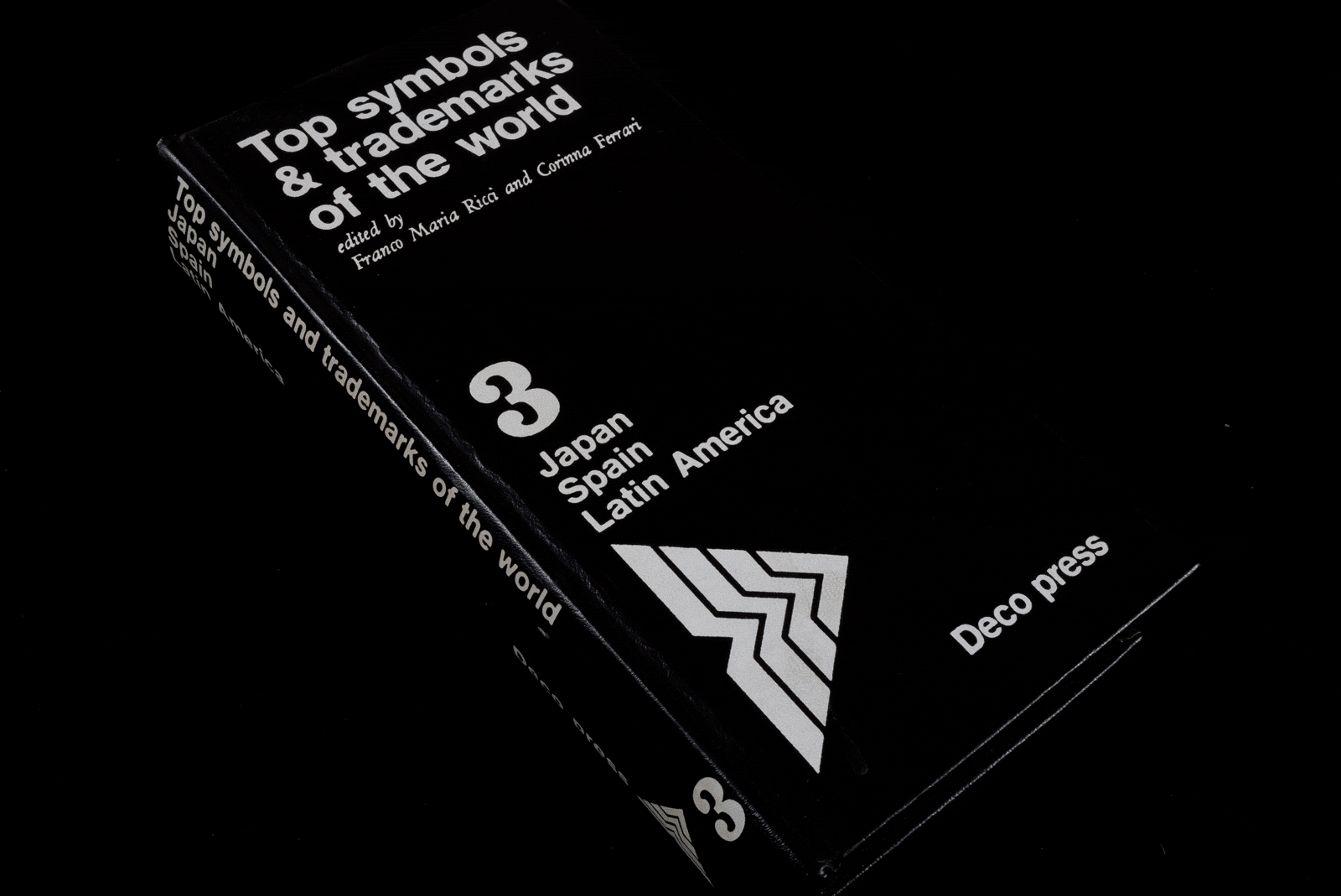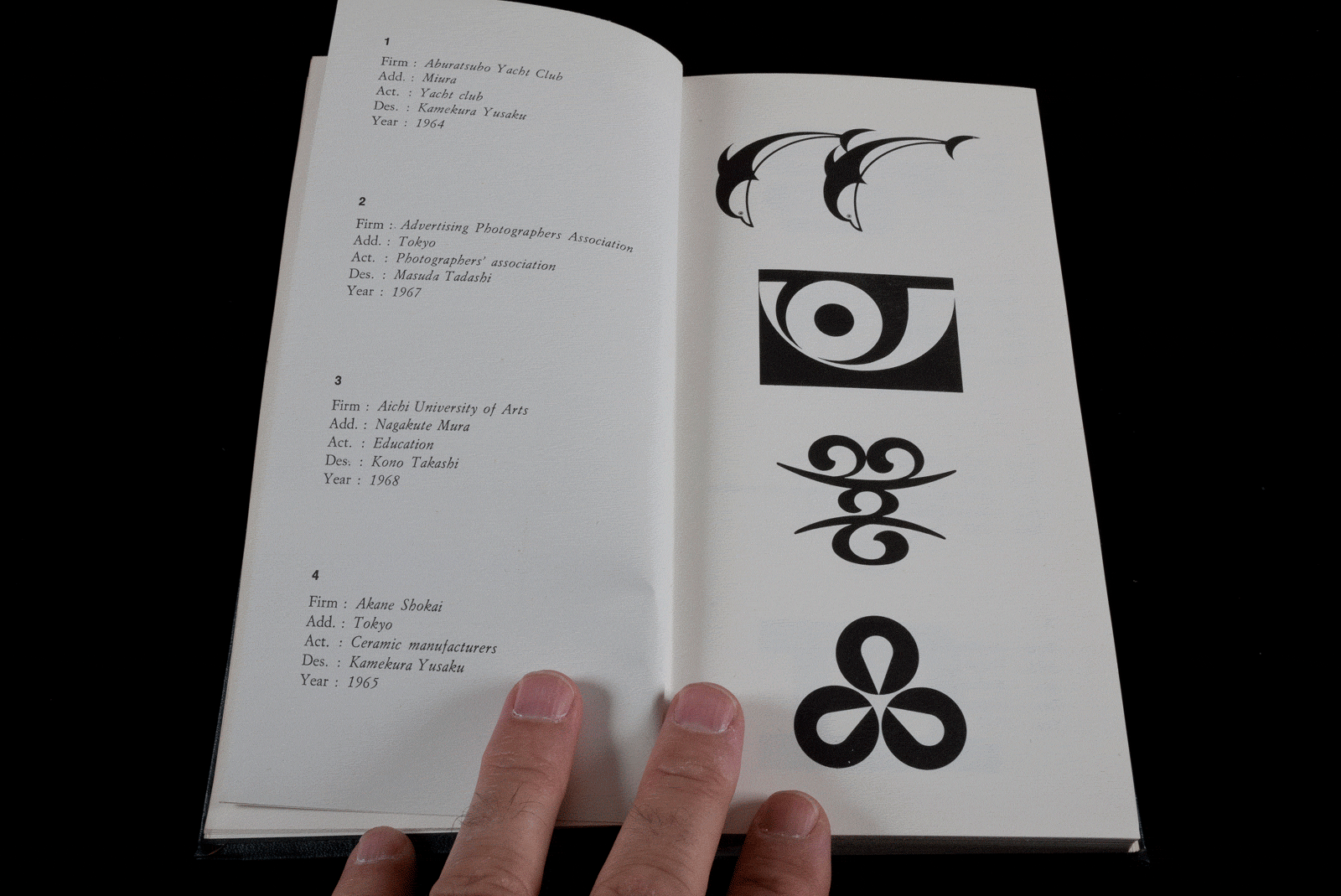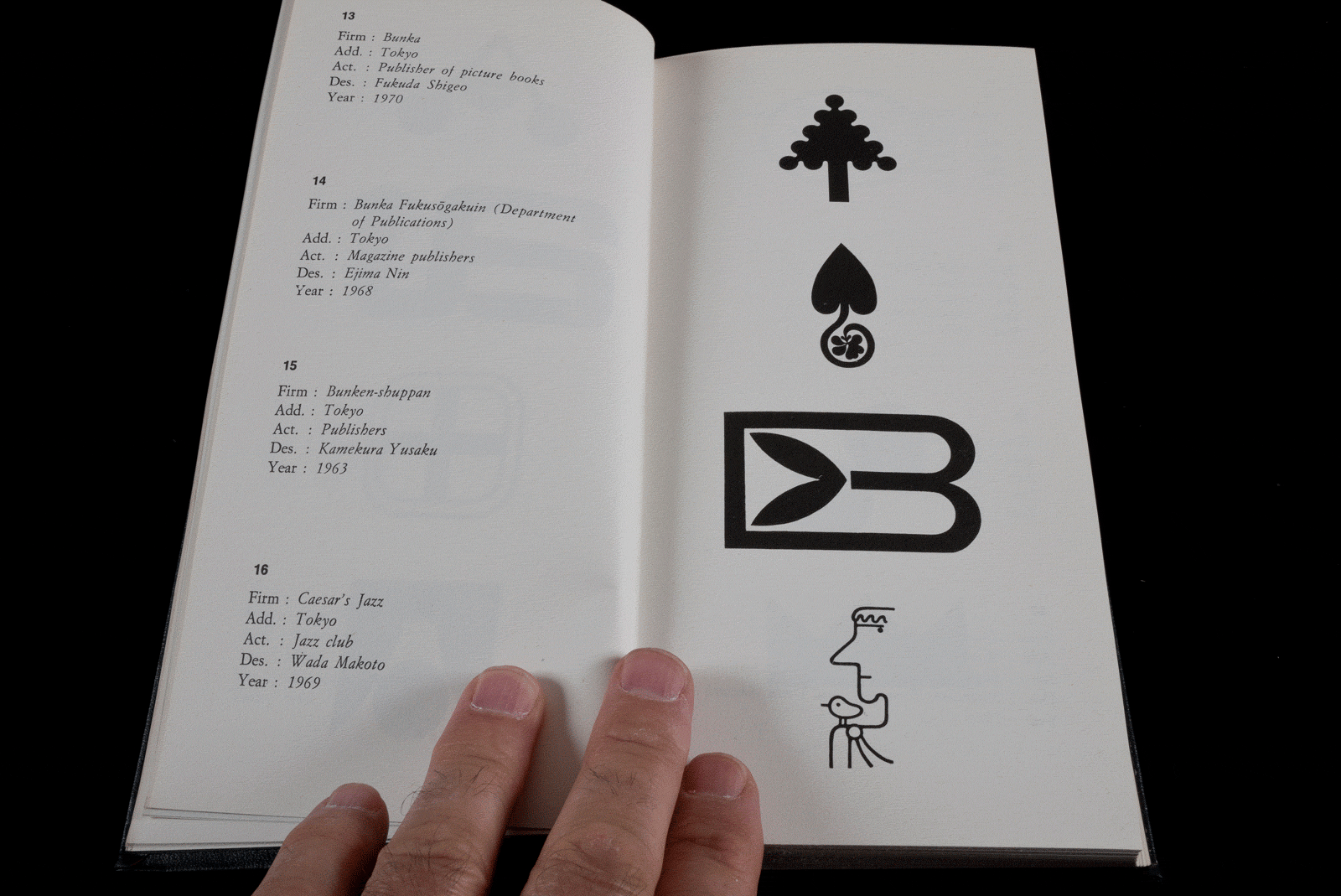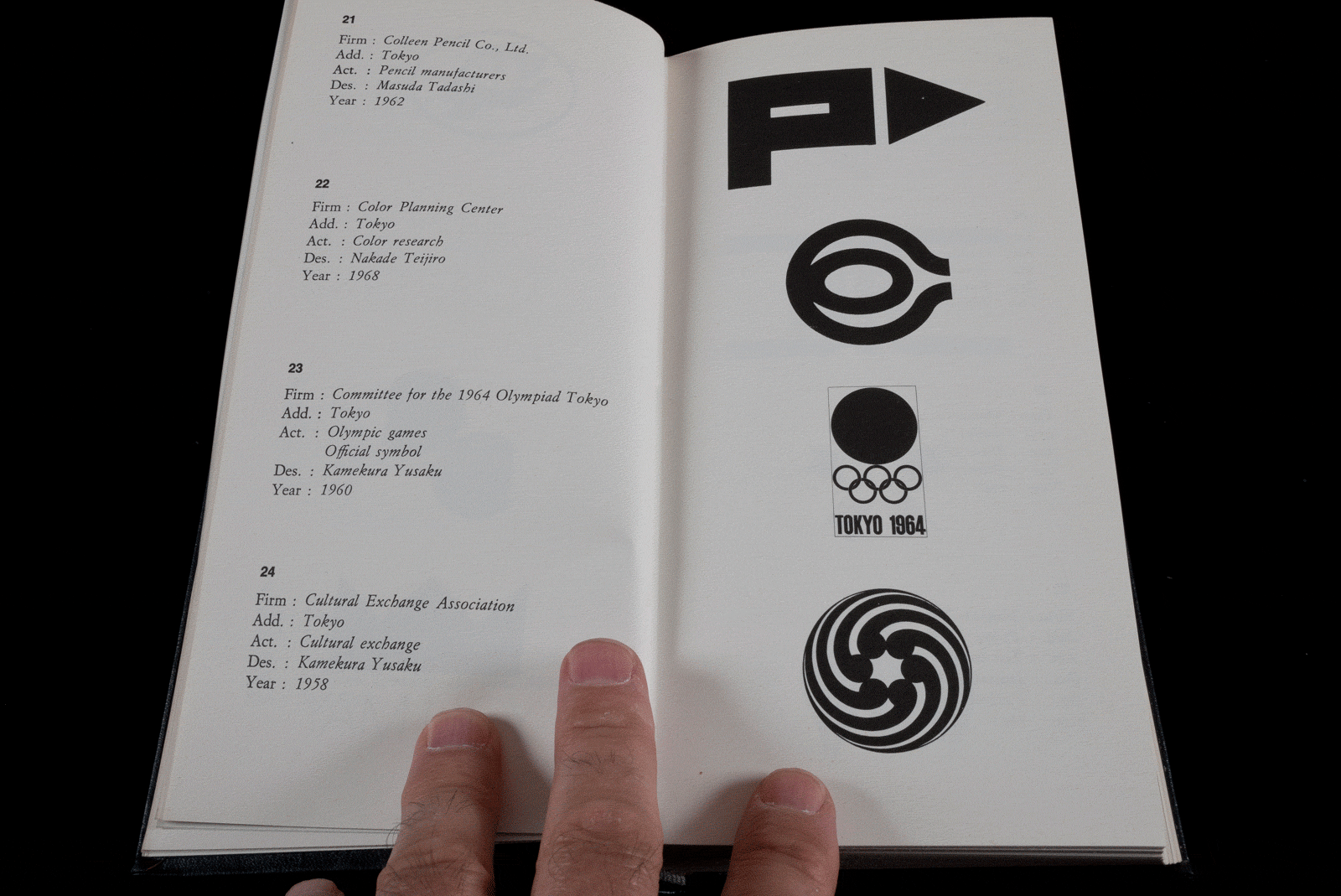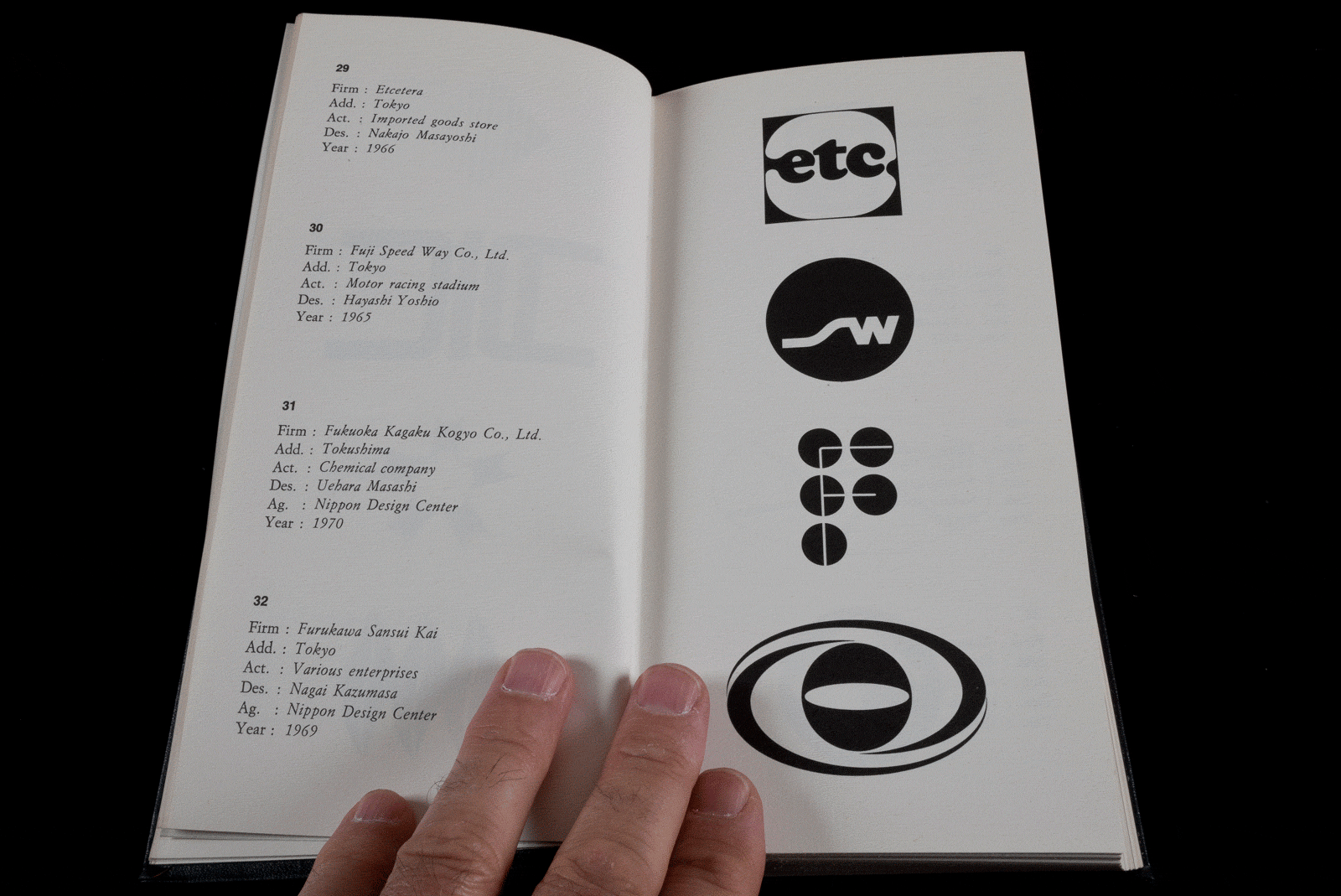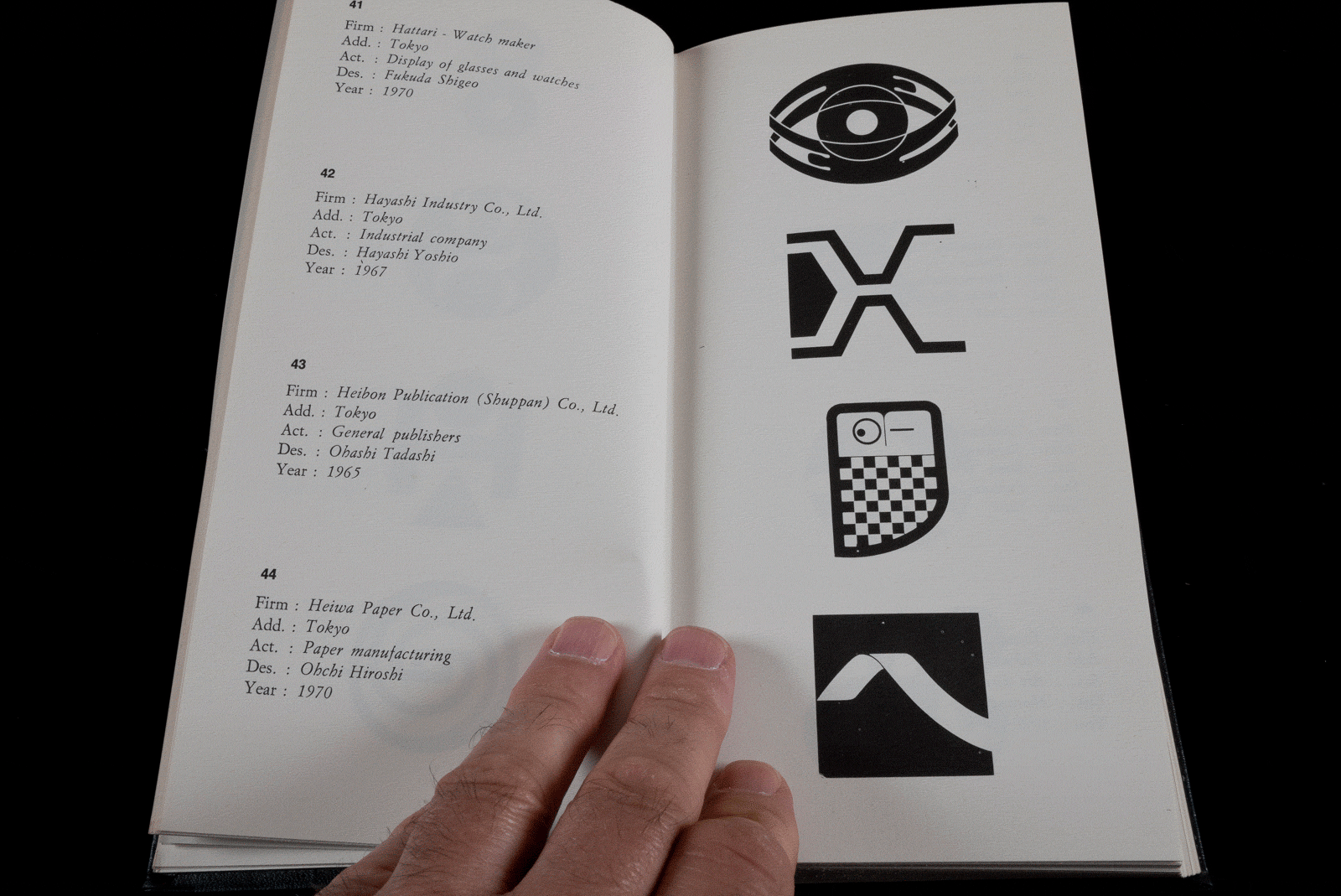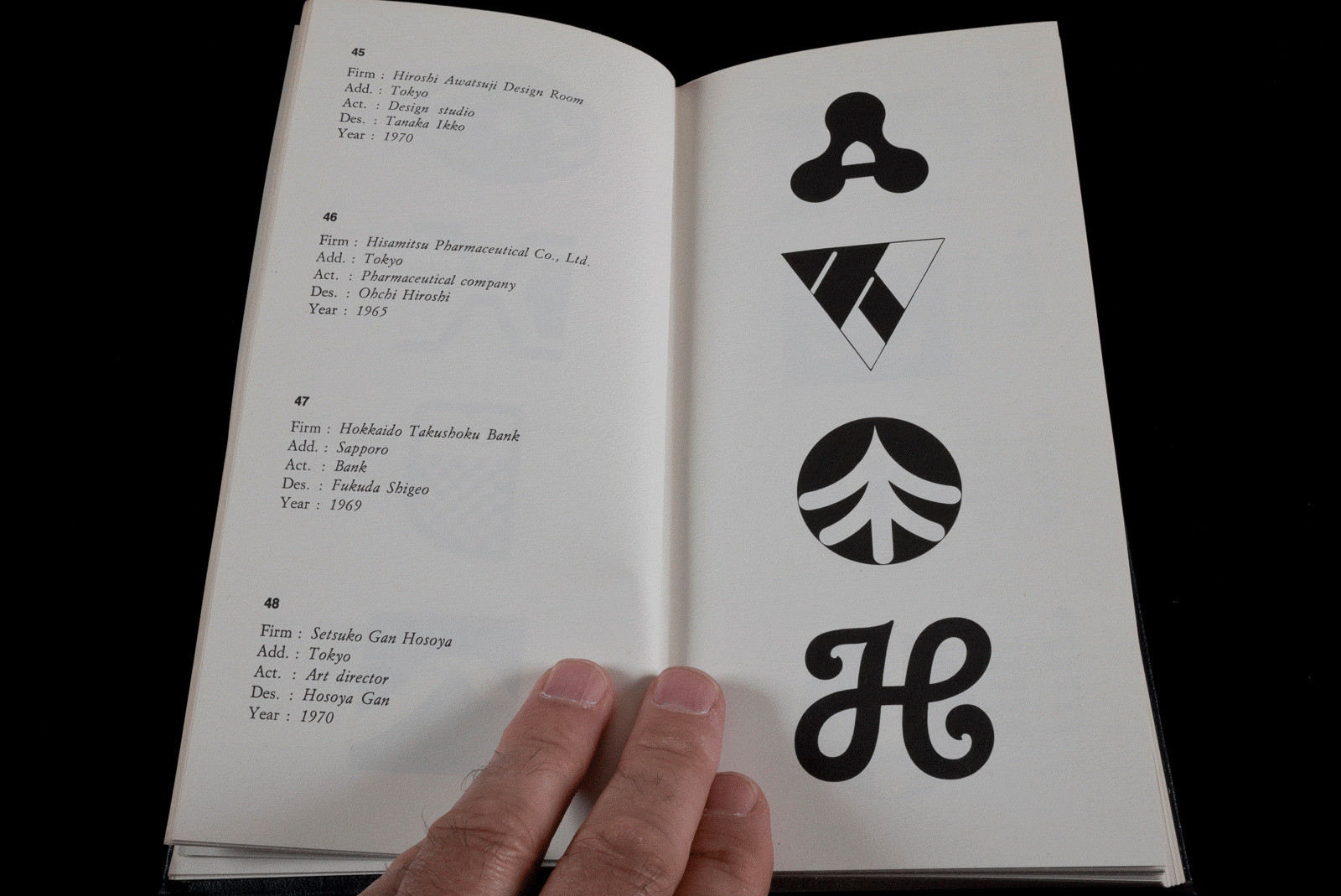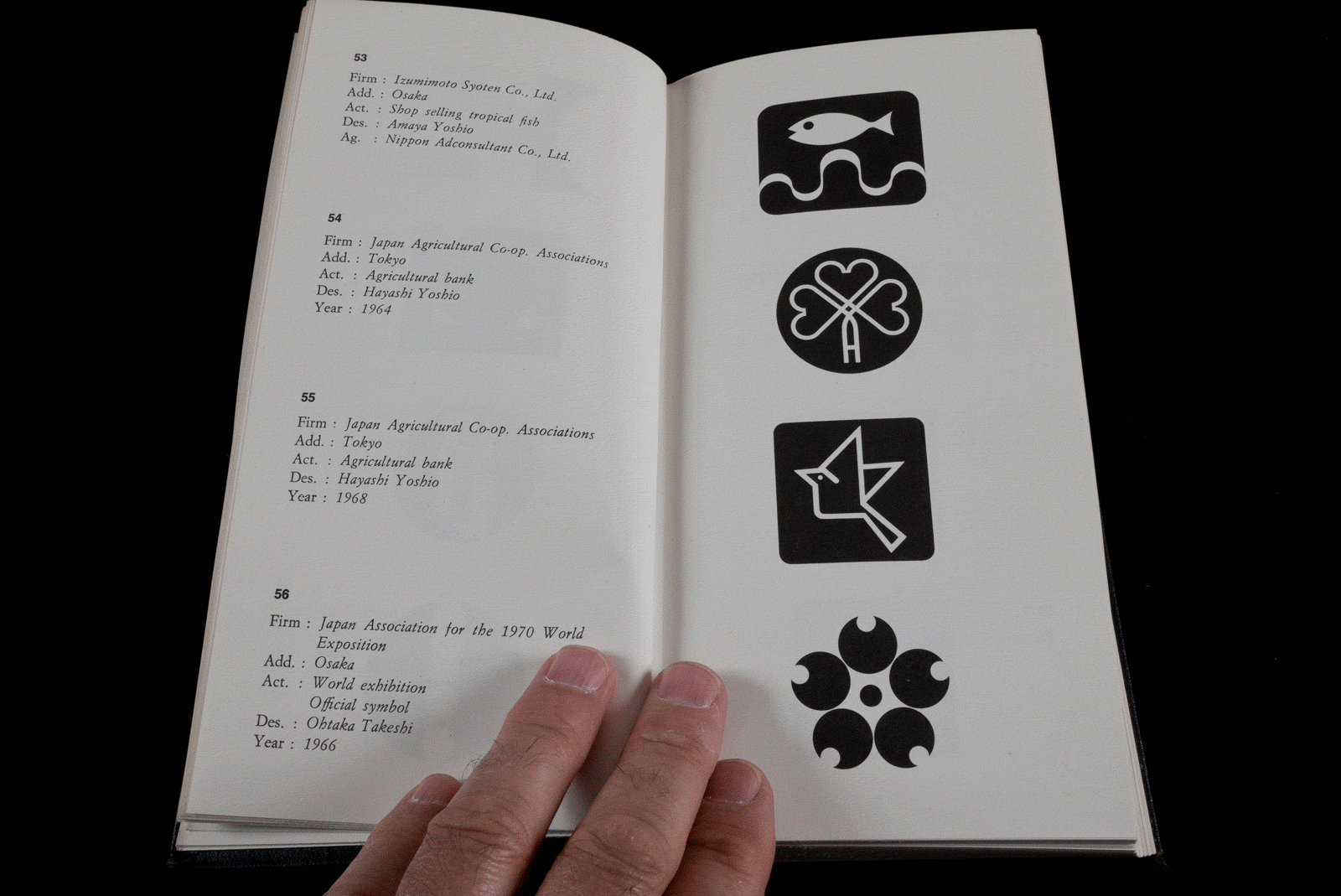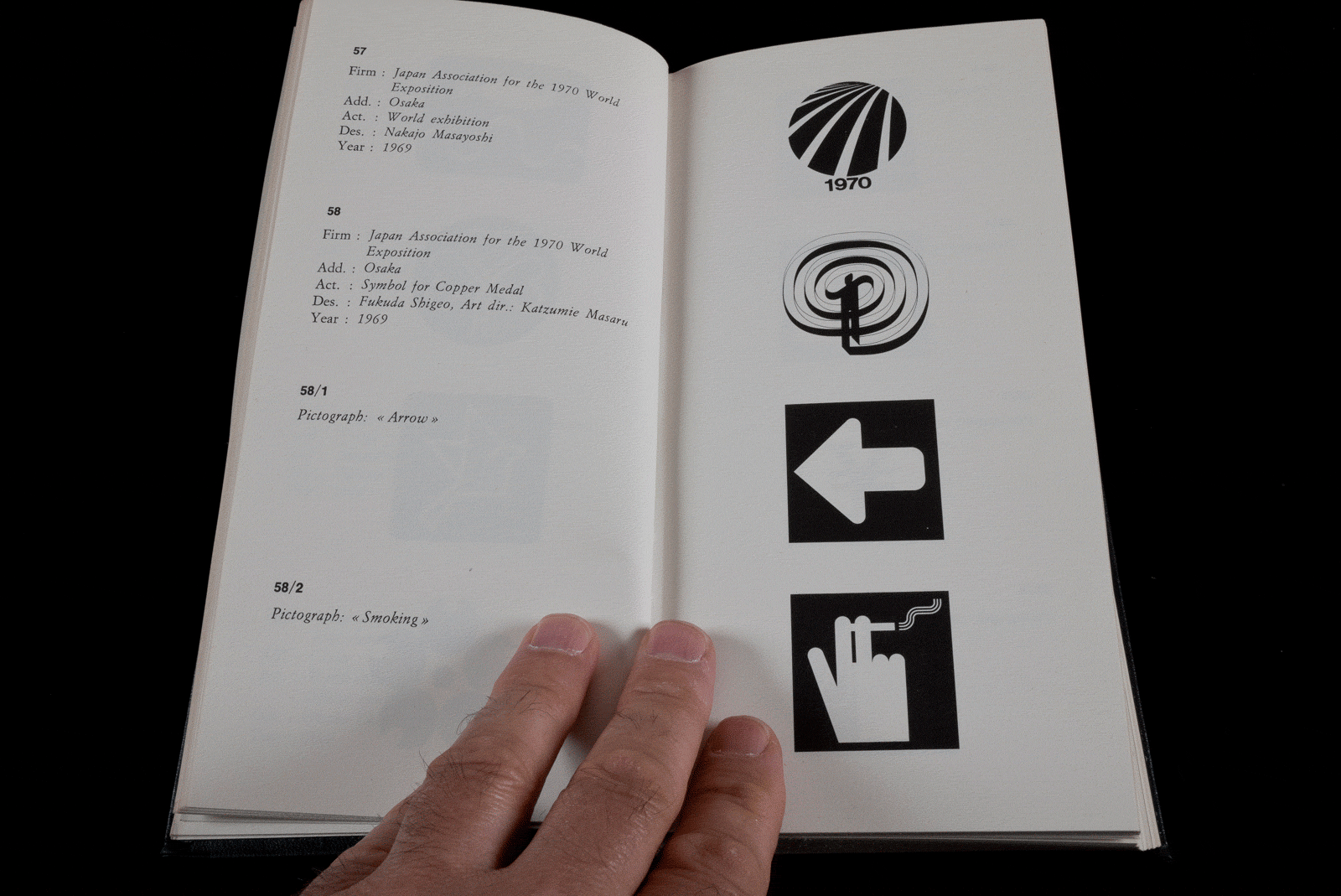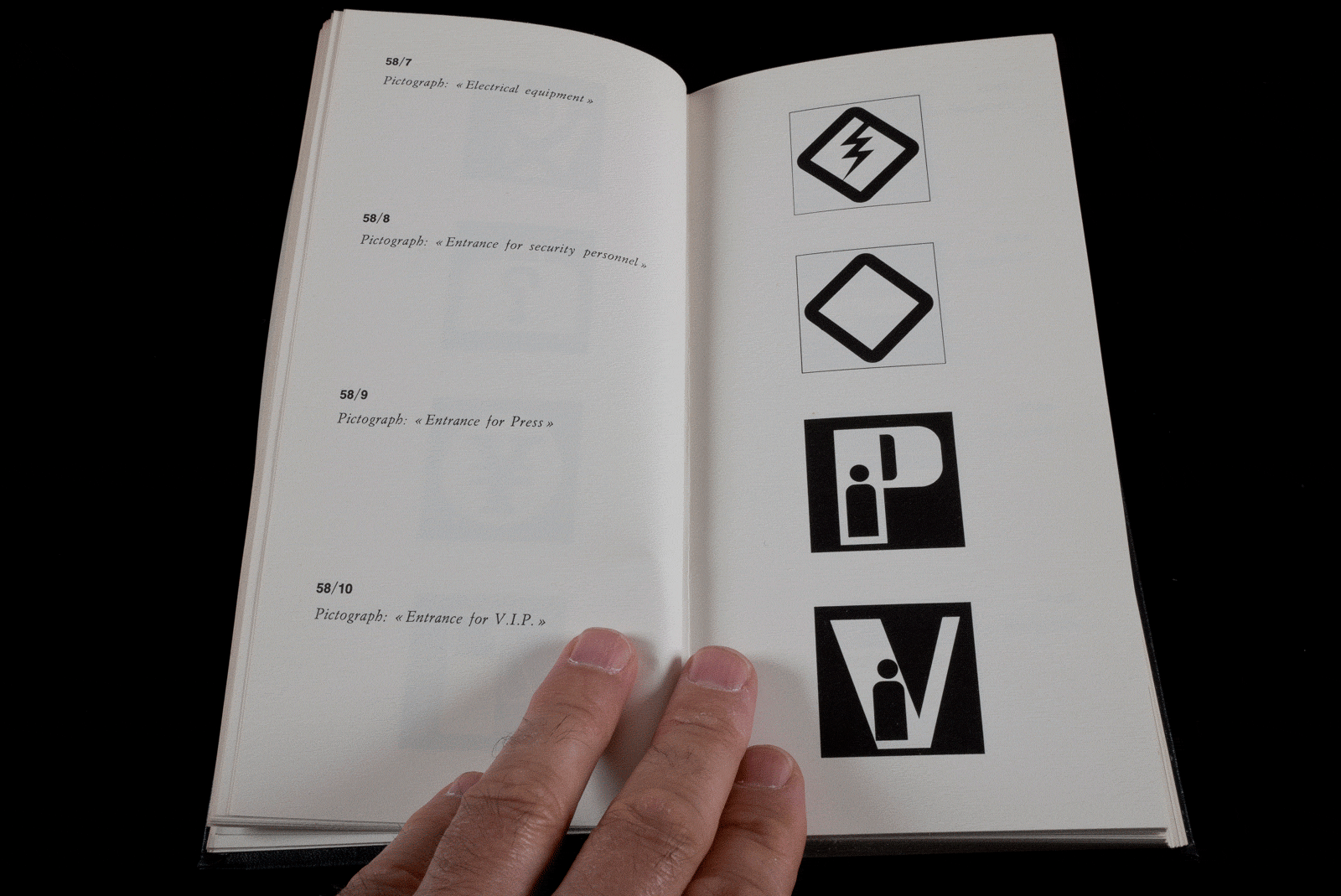
Top Symbols & trademarks of the world | Vol.3
Franco Maria Ricci & Corinna Ferrari | Top Symbols & trademarks of the world | suite
Voici venir le 3e Vol de la collection Top Symbols & Trademarks of the World. Le volume 2 se trouve ici . J’avais publié le 5 mai 2006 le premier volume d’une collection de 10 albums édités par Franco Maria Ricci et Corinna Ferrari en 1973. Voici aujourd’hui présenté le deuxième volume de cette somme assez incroyable par le foisonnement, la richesse des ressources et la rigueur quasi encyclopédique déployée par les deux auteurs sus-nommés.
Ce n’est pas moins de 300 pages et environ 600 trademark dont il s’agit là. La fin des marques des USA (publiés dans le premier volume) et une quantité impressionnante de marques venant du Canada. Chacun des trademarks se trouve accompagné de la nomenclature de ses créateurs: le Client, son origine géographique, son secteur d’activité, le Designer et l’Agence en charge du budget ainsi que l’année de sa création. On imagine sans peine la logistique nécessaire à ce travail à une époque où Internet n’existait pas encore, et que le Fax venait juste de naitre sous une forme artisanale qui n’a rien à voir avec les technologies d’aujourd’hui (rapidité, laser, multi-envoi etc.). Il est à parier que tout ce travail organisationnel a été effectué par courrier postal et peut-être par téléphone (j’en doute).
Rendons donc hommage à ces deux auteurs d’avoir commencé et terminé quelques mois plus tard la publication de près de 6000 signatures d’entreprise parfaitement recensées et légendées.
Il serait parfaitement superfétatoire de ma part de vouloir analyser chacune de ces marques, travail titanesque auquel je ne me risquerai même pas. Cependant il apparait nécessaire de dégager quelques grandes lignes de cet expression graphique.
Tout d’abord qu’est ce qu’un logotype. Contrairement aux idées reçues, ce n’est ni le symbole, ni le sigle ou acronyme, très exactement il s’agit de l’écriture intelligente c’est à dire qui fait sens de la marque. Sony, Apple, Kodak, ou Wolkswagen (etc.) se sont dotés d’un arsenal de signifiants dont un logotype.
L’ensemble Symbole + Sigle + Logotype constitue un tout rassemblé sous le terme générique de bloc-marque. Sans compter des extensions de ce système lorsqu’une marque se dote d’une marque ombrelle. Nous y reviendrons.
Lorsqu’on examine à la loupe chacun de ces trademarks on constate presque toujours un certain nombre de constantes.
Une bonne marque n’est pas bavarde. Elle résume de la façon la plus simple le métier, les valeurs, l’environnement industriel et/ou le secteur d’activité de l’entreprise ou de l’institution. Il est à parier que chacune des créations ainsi rapporté a fait l’objet d’une démarche réflexive où le client et son agence/designer ont analysé de la façon la plus claire et évocatrice le message que doit délivrer la marque. On peut aussi parler de poésie de la marque, par sa simplicité minimaliste elle rappelle cette forme d’écriture cher au Japon le haiku, qui ne s’embarrasse d’aucune circonvolution verbale.
Nombre de créations se contentent d’assembler graphiquement deux ou trois lettres. Nous disons graphiquement lorsque cet assemblage subtilise au passage toute forme typographique inutile à la compréhension d’un sigle ou d’un acronyme. Ainsi par exemple le ‘RJR’ dessiné par Walter P. Margulies en 1969. Bien entendu la poésie des marques s’exprime plus évidemment dans la recherche d’un symbole significatif, c’est le cas de la marque ‘FONDA’ dessiné par Dixon & Parcels Associates.
Chacun sait qu’il faut chercher l’origine de cet art du ‘résumé’ de l’image de l’entreprise dans la symbolique des blasons, la science de l’héraldique. Mais alors que cet art remonte à l’époque antique, son propos était tout autant d’affirmer la puissance d’un seigneur à une époque où les rois tiraient leur légitimité de Dieu que de servir aux nobles artisans d’enseigne pour leur métier. Sorte d’écusson païen qui se devait de rappeler au chaland l’exercice d’une profession hautement respectable.
C’est donc le XIXe siècle, et surtout le XXe qui voyaient le développement de l’industrialisation qui donnèrent à cette forme d’expression graphique ses lettres de notoriété. Là il s’agissait de marquer des produits distribués par milliers puis par million. Là il s’agissait de publier des ‘réclames’ puis des publicités portant l’enseigne, la marque de l’entreprise.
Il existe des modes dans cet expression. Elles tiennent autant aux outils de conception (crayon, gouache, carte à gratter) qu’aux médias qui les véhiculent. Le Print et l’architecture corporate ont développé des modes dont témoigne cet ouvrage de Franco Maria Ricci. Les trademarks s’exprimaient d’abord en noir et blanc et se devaient de ‘fonctionner’ de la sorte. Sans l’aide chatoyante de la couleur. On verra que depuis près de trente ans l’arrivée d’un univers d’écran translucide (ou trans-lucide) a formatée l’expression graphique des marques en couleur, se servant à la fois de transparences et d’effets de brillance. (cf la nouvelle marque de Rank Zerox). Il s’agit sans doute d’une tendance lourde et d’une véritable rupture avec la première époque des logotypes et marques. (Bien qu’on puisse voir dans les écussons en métal les prémices de cette tendance moderne). Je vous laisse découvrir les quelques pages qui suivent.